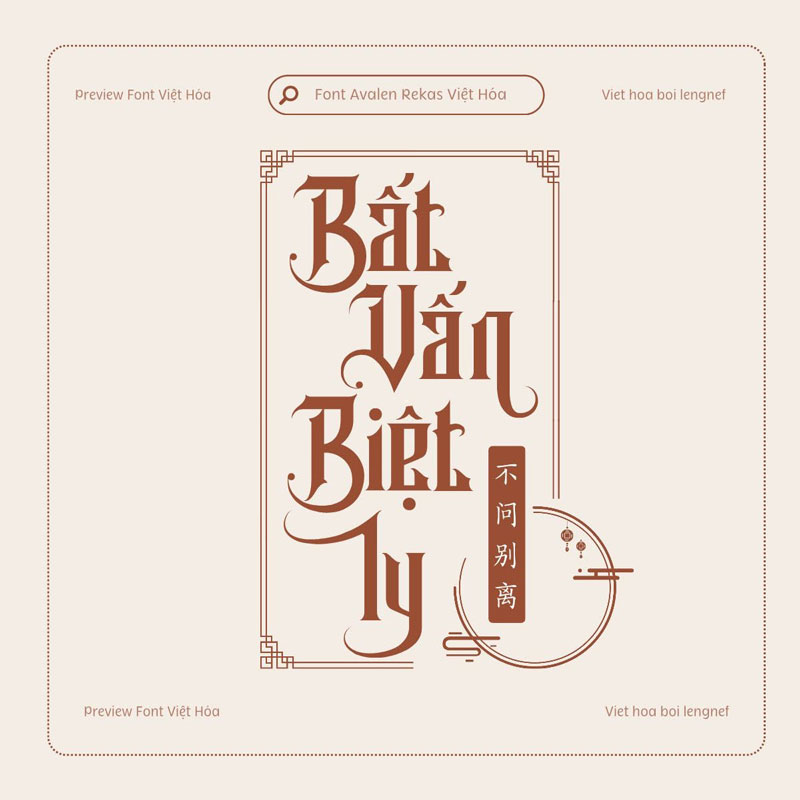
• Tác giả: StringLabs Creative Studio
• Việt hóa: lengnef
Font LF Avalen Rekas Việt hóa
Avalen Rekas là một phông chữ gothic hiện đại được thiết kế để sử dụng trong logo, quảng cáo thời trang hoặc tiêu đề và quảng cáo.